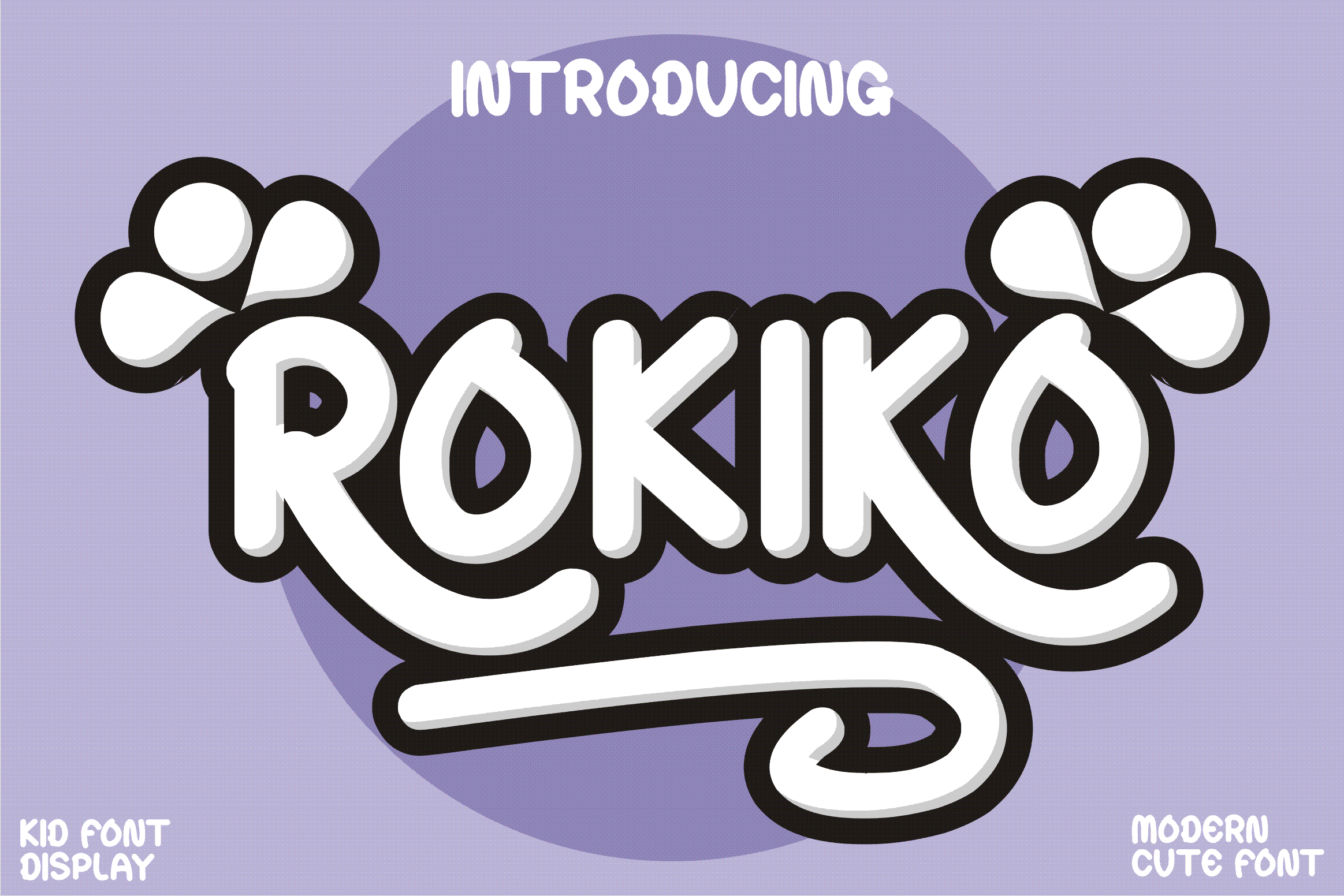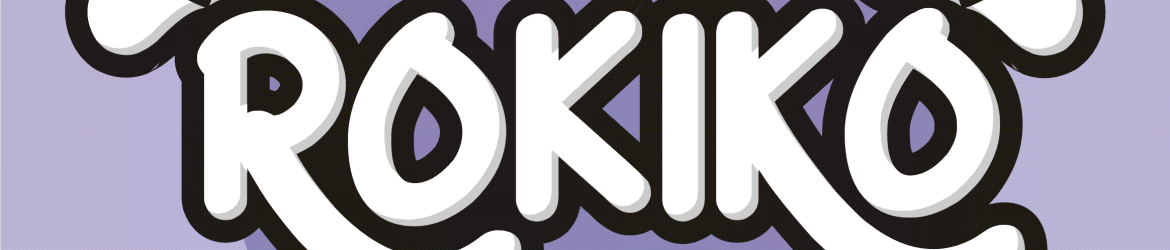
Rokiko Font – Download Grátis
A Rokiko Font é uma escolha ideal para quem busca um tipo de display que combine elegância com alegria. Esta fonte é perfeita para criações infantis, desde jogos até quadrinhos, e também serve bem em design de livros e cartazes. Suas linhas curvas e suas formas suaves são adaptáveis para qualquer situação, permitindo criar mensagens que expressam um toque de alegria e descontração sem perder sua elegância. Seja você um designer criando uma identidade visual ou alguém fazendo uma simples assinatura em um projeto pessoal, Rokiko será uma escolha sólida para aqueles buscando uma fonte com a qual possa experimentar a diversão de criar mensagens mais coloridas e vivas. Sem dúvidas, ela será um grande complemento para qualquer trabalho que você está desenhando.